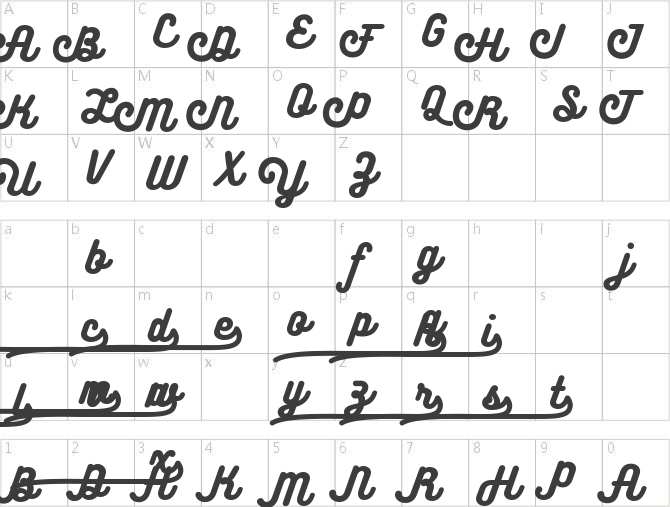
BukhariScriptAlternates 詳情頁(yè)
BukhariScriptAlternates字體字庫(kù)是一款讓人賞心悅目、百看不厭的英文字體,適合各類廣告和產(chǎn)品包裝設(shè)計(jì)應(yīng)用,字體大小0.03MB,格式為ttf字體,上傳用戶是白刃寒走得慢,作者/版權(quán)方為未知